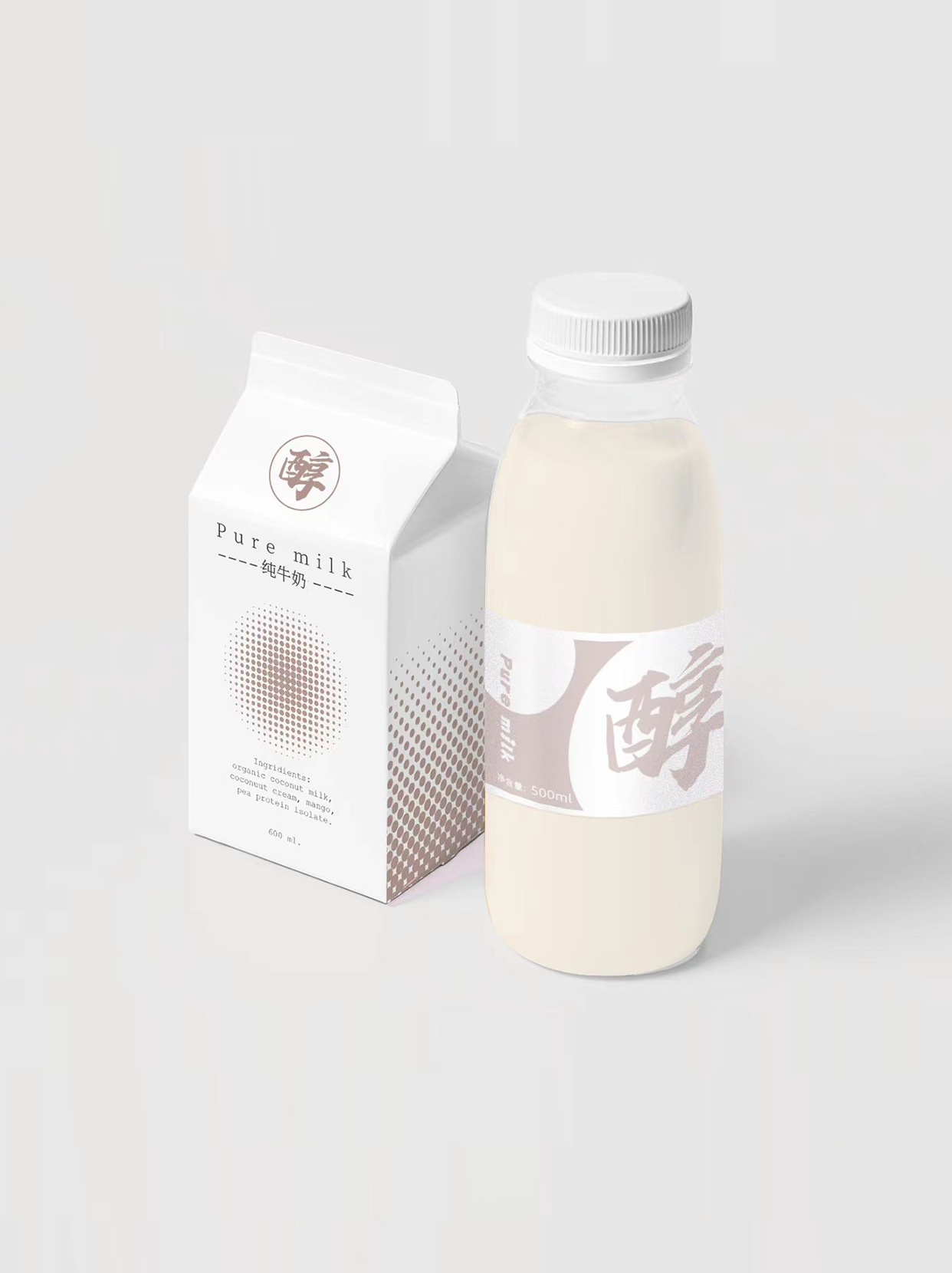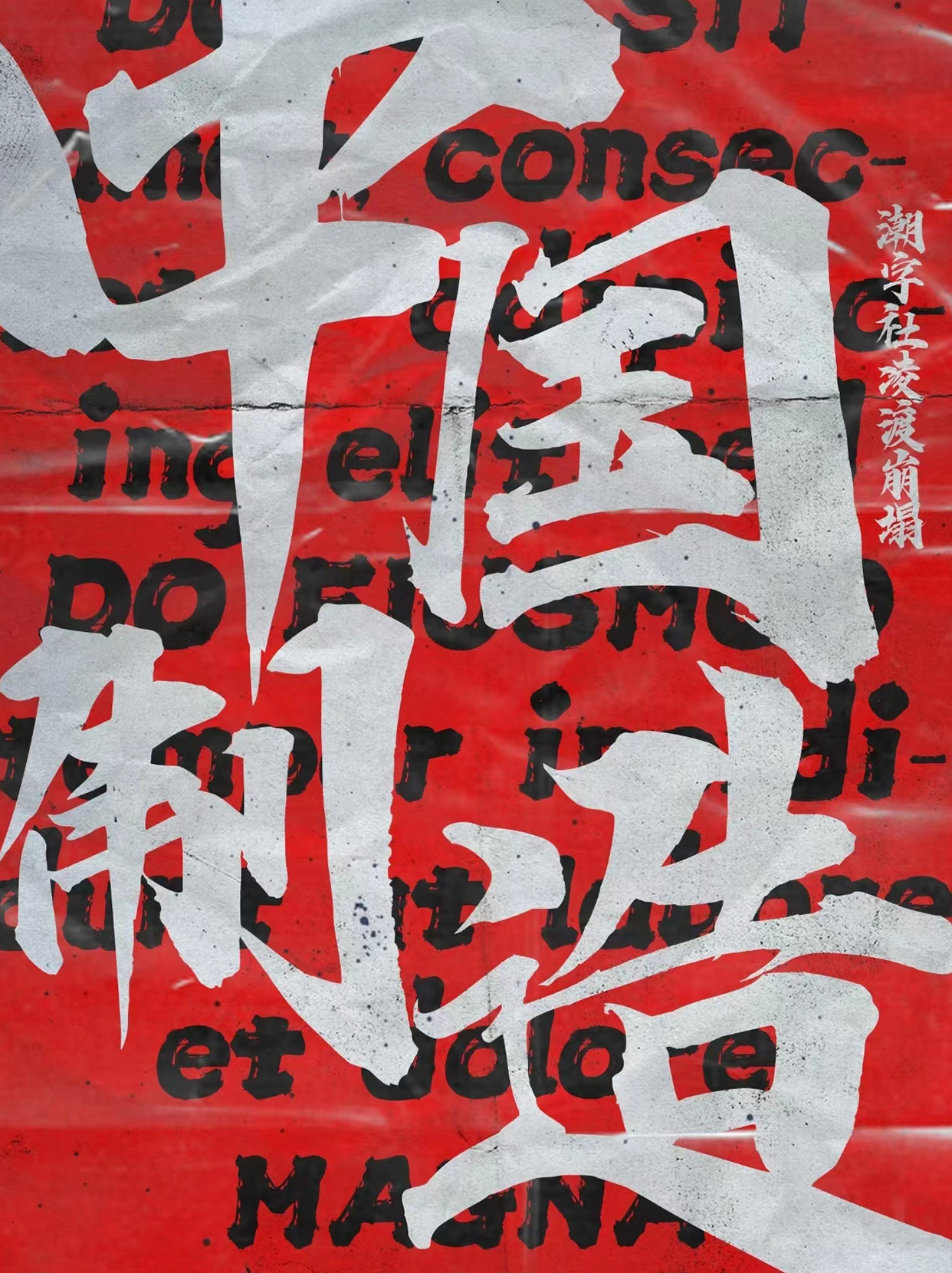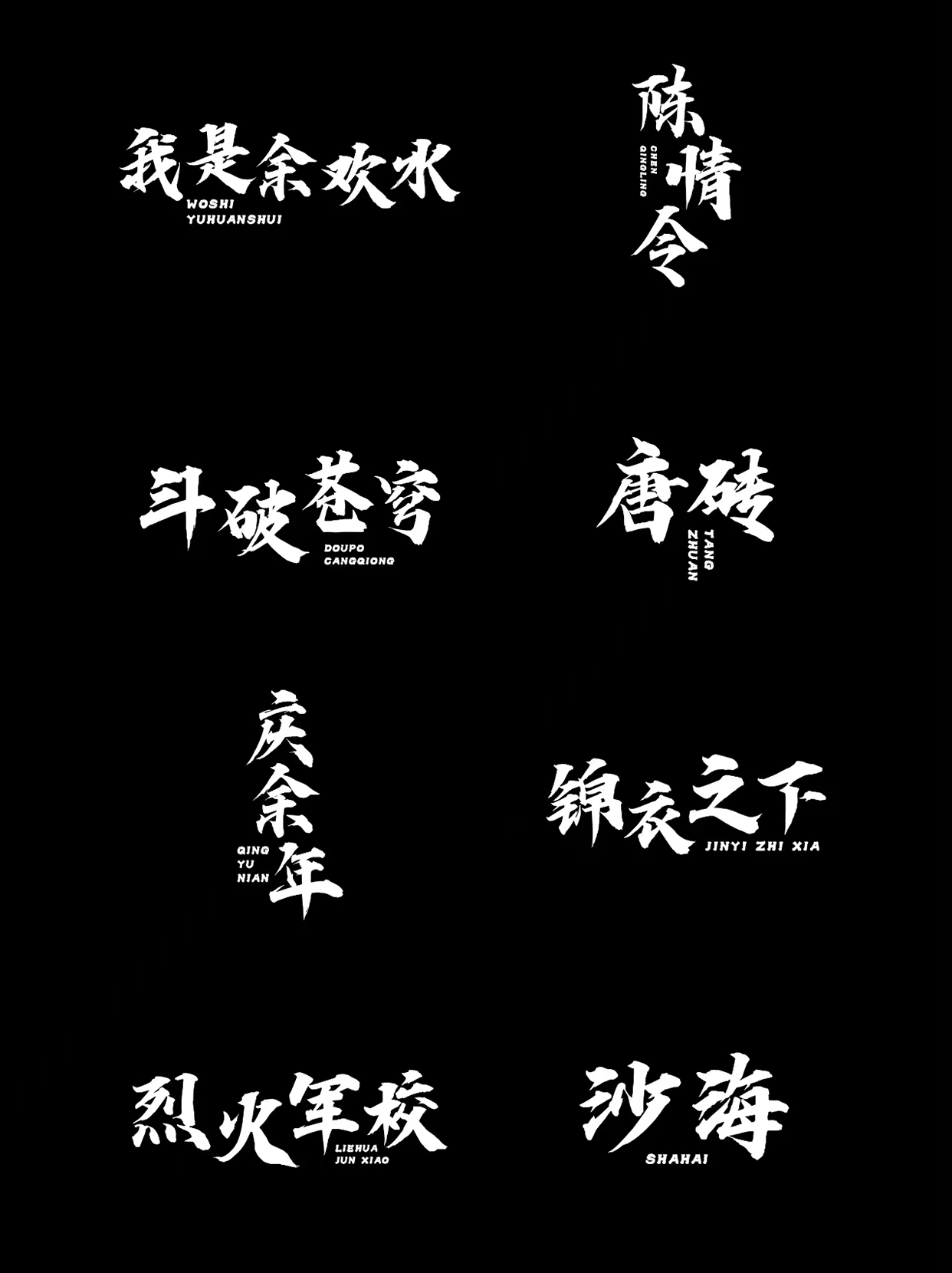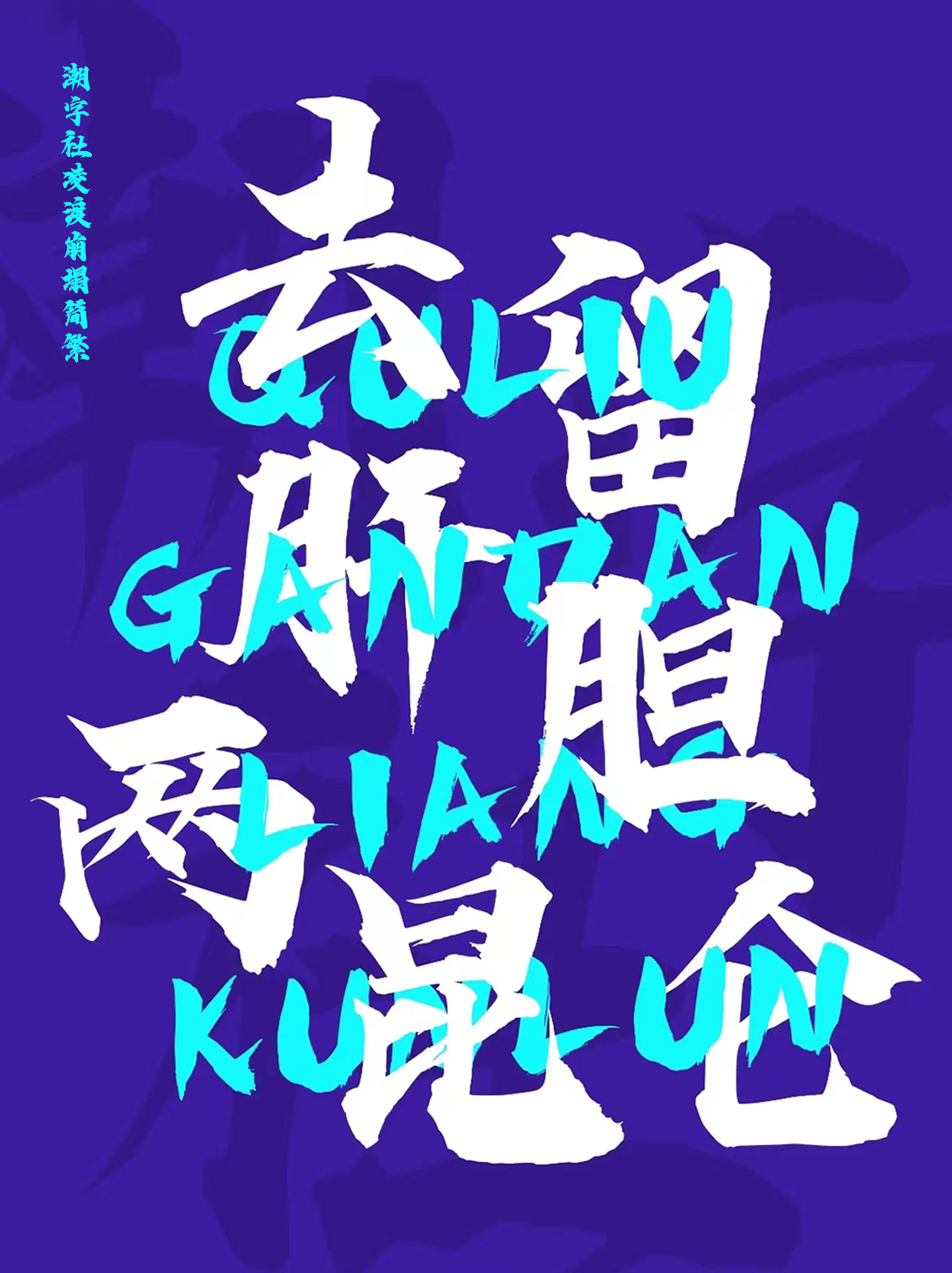
字体笔画稳健,起笔处果敢潇洒,转折处短促有力,毫端处风虎云龙,在体现张力的同时,微妙细致的转折在细节上收敛体现,使字体整体上张弛有度,潇洒自如,起笔自由潇洒,落笔苍劲有力,点画疏密相间,走势生动顿挫,颇具不受羁绊,先锋无畏的潮流气质;整套字体既符合传统书法的笔法与结构,又具有视觉设计张力,运笔抑扬顿挫,生动传神,观其力而不失,身姿展而不夸,笔酣墨饱,粗细变化自然给观者带来流云流水般的顺畅。